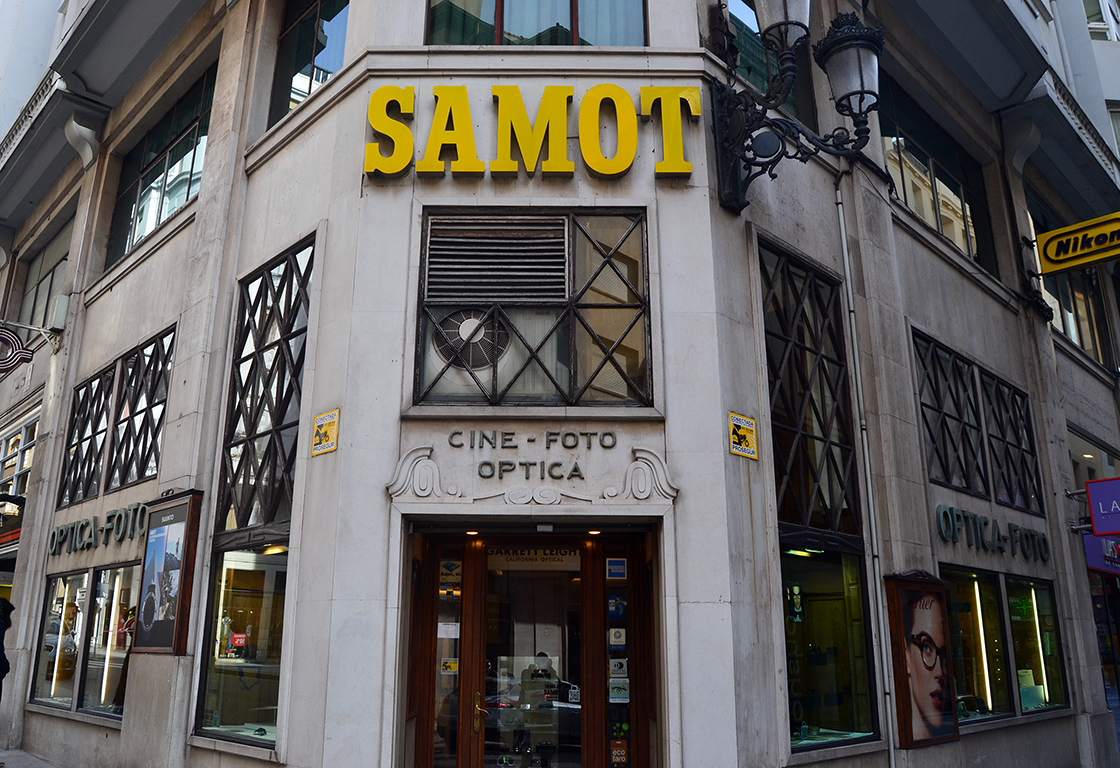
Letras de SAMOT
A partir de ahora a los rótulos rescatados se añadirán  las letras «Optica – Foto» que han adornado las fachadas de San Francisco y Lealtad desde el año 1945 cuando se instaló ahí SAMOT hasta que recientemente han reformado su local, pero han mantenido la esencia de su historia y conservado su rotulación. Este material ha sido donado al proyecto por Guillermo, tercera generación al frente de la centenaria óptica. Son un juego de letras de gran formato en latón. cada pieza mide 22 x 30 cm.
Foto anterior a la reforma donde se ve la ubicación de las letras. (Santatipo, 2015)